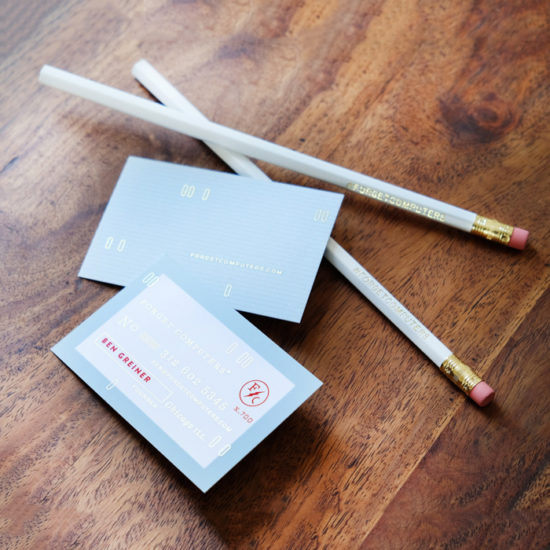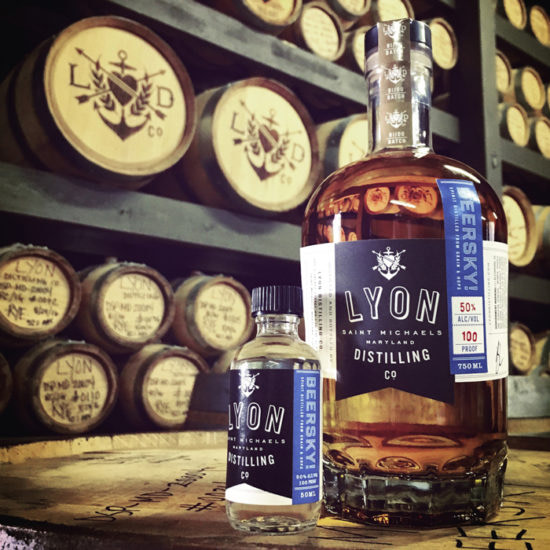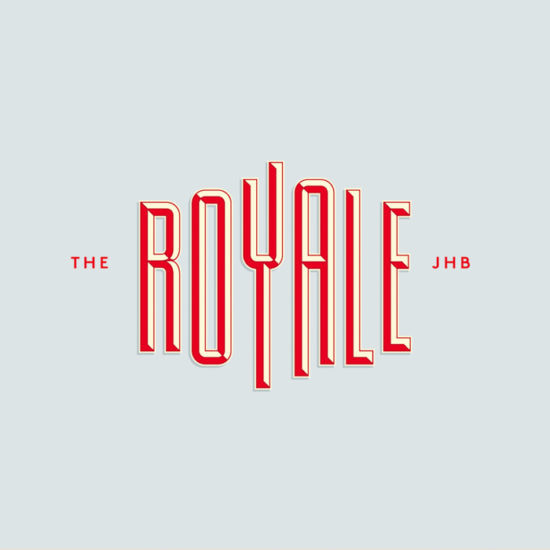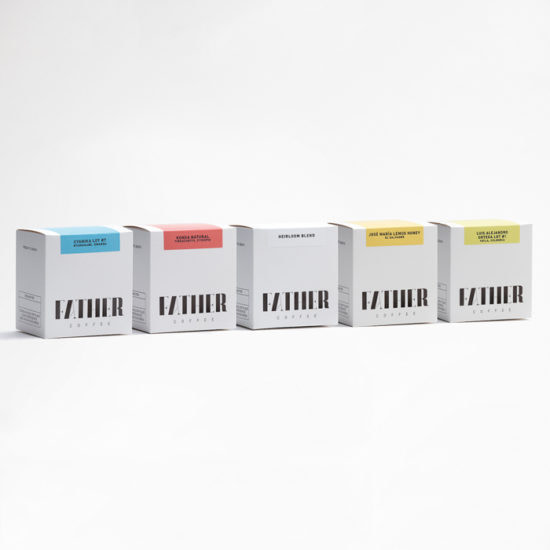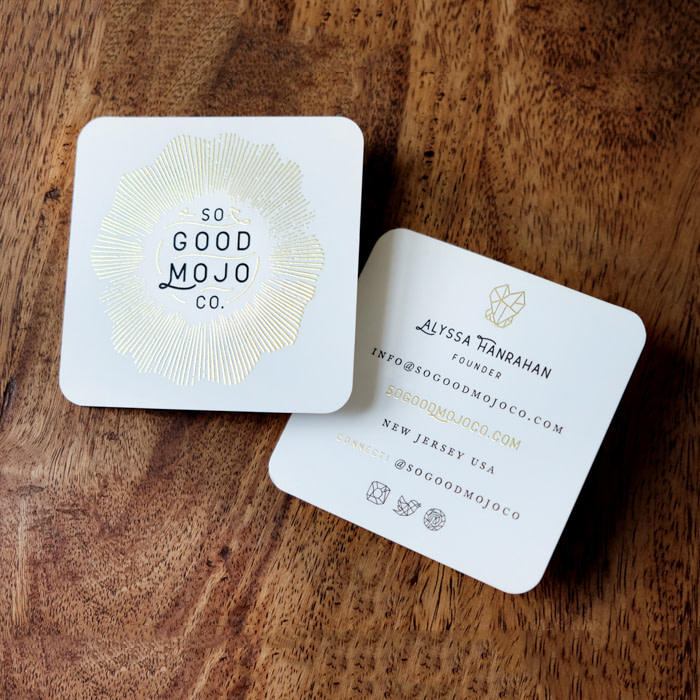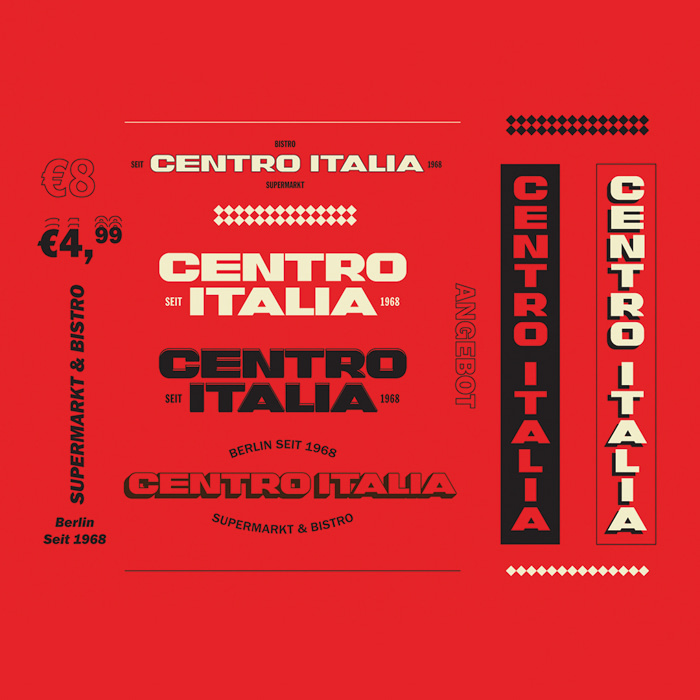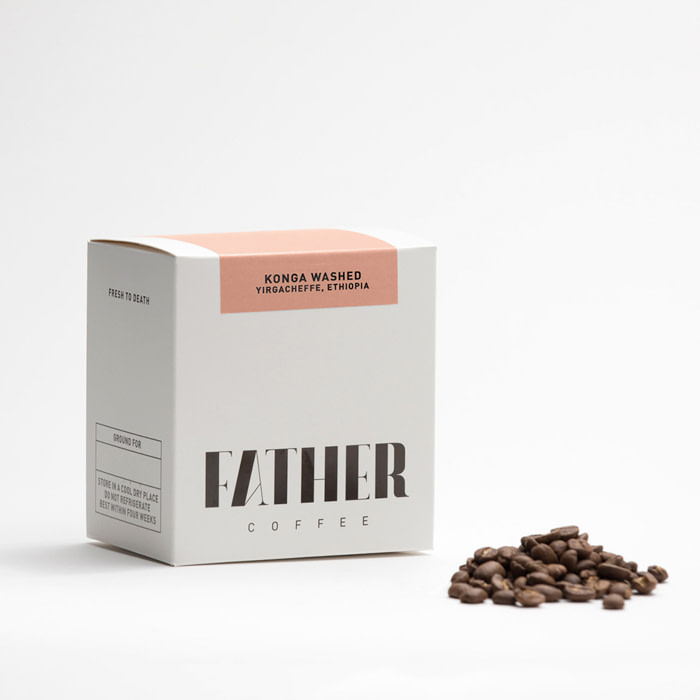
3 designer con il pallino per i font
Quanto c’è di un marchio in un font? Il motto di questi tre designer è: la parola ai font.
Cosa nasce dall’incontro fra arte tipografica e stampa di qualità? Nei Biglietti da Visita creati da questi 3 designer, i protagonisti sono i font.
Non è facile raccontare una storia all’interno di un design. Ma grazie a una miriade crescente di font nuovi di zecca, oggi i designer hanno la chance di sperimentare modalità di comunicazione inedite e originali. Il motto di questi tre designer è: la parola ai font.
Funnel
Funnel è il frutto del lavoro di Eric Kass, designer con sede a Indianapolis. Dopo anni e anni trascorsi chino sulla scrivania di un’agenzia di design, Eric si è reso conto che quello che voleva davvero era dedicare a un marchio tutto suo la cura e la passione che fino ad allora aveva riservato ai marchi dei clienti più svariati. Ispirandosi alla sua variegata collezione di stampe vintage, caratterizzate da font eclettici, Eric ha dato vita all’identità visiva di Funnel, basata su un logotipo esclusivo e font classici in abbondanza. Questa esuberante varietà tipografica esprime, per Eric, l’amore per i dettagli e il rispetto della tradizione del design.
Quando Eric si mette al lavoro sul progetto di un cliente, per prima cosa cerca di visualizzare la storia del marchio identificandone gli elementi distintivi. “Mi piace scomporre il marchio in un sistema di segni, font, colori ed elementi che danno vita al linguaggio del marchio stesso, alla sua essenza, alla sua storia”, afferma Eric. “È il primo passo, il resto viene da sé: cancelleria, sito internet, design d’interni e materiale stampato”.
Per esprimere al meglio l’identità del suo marchio, Eric ha selezionato una gamma di font e finiture che non passano inosservati. Grazie ai Biglietti da Visita con finitura Soft Touch e Stampa a caldo Oro, oggi l’immagine di Funnel risplende più che mai. “L’unicità della tipografia e del design si abbina alla finitura satinata della carta e ai rilievi dorati. La gente non solo si incuriosisce, ma vuole saperne di più”, afferma Eric.
Nicholas Christowitz
Prossima tappa: Berlino, il palcoscenico dell’astro nascente di Nicholas Christowitz. Nato e cresciuto a Johannesburg, in Sudafrica, Nicholas si è trasferito in Germania con la ferma intenzione di immergersi nel panorama artistico locale e perfezionarsi come designer. Nel 2014 ha fondato uno studio di consulenza di design, e da allora ha avuto un cliente dietro l’altro.
In una città come Berlino, con i suoi mille stimoli dal punto di vista del design, per Nicholas è stato naturale mettere alla prova la sua creatività. Negli anni, ha inanellato una serie di font assolutamente magnifici: il suo fidato archivio si arricchisce ogni volta che si mette al lavoro sul progetto di un cliente. “Ho un vero e proprio patrimonio di font e stili che consulto all’inizio di ogni progetto”, ci racconta Nicholas. “Di solito seguo l’istinto, aspetto la proverbiale scintilla”.
I Biglietti da Visita Luxe di Nicholas sono una rappresentazione tangibile di quel che si dice “lasciare la parola ai font”. Per le informazioni personali e la biografia ha scelto il font Plantin. “Ho letto assiduamente per anni la rivista Monocle, e alla fine mi sono innamorato di quel font. È semplice, elegante e piacevolmente neutro”, ci spiega Nicholas. Anche la personalità di Nicholas, semplice e sicura di sé, trova espressione nei biglietti Luxe: “Il cartoncino spesso trasmette ai clienti le mie priorità: qualità, consistenza e percezione”.
BK + Co.
BK + Co. è uno studio creativo che opera a Richmond, in Virginia. Fondato da Birdgit Kreutzer, lo studio collabora con imprenditori dalla personalità creativa: l’obiettivo è dare vita a un’identità visiva inconfondibile per ogni marchio, in grado di raccontarne la storia. Bridgit ha studiato design alla Virginia Commonwealth University e alla prestigiosa Gerrit Rietveld Academie di Amsterdam. La sua passione per il design l’ha spinta a creare un’attività tutta sua, con l’ispirazione e il sostegno della comunità di creativi di Richmond. “Qui la norma è esplorare strade nuove, sostenendoci a vicenda”, racconta Bridgit.
Aprire uno studio di design si è rivelato una scelta appagante. “Lavorare e collaborare con i clienti è un privilegio, per me. Ogni nuovo progetto è una sfida a sé stante, che mi stimola a giocare con nuove idee”. Tutti i progetti sono diversi fra di loro. Il primo passo, per Bridgit, è concentrarsi sul font.
Di recente ha lavorato su un progetto per un massoterapista. Il cliente desiderava un design che trasmettesse calma, tranquillità e l’idea di un legame genuino con la natura. Bridgit ha optato per un carattere tipografico classico e pulito: il complemento ideale per il resto della grafica, improntato alla semplicità. Per la stampa ha scelto i Biglietti da Visita Luxe, la cui finitura opaca si sposa ai colori tenui del marchio. “Guardando questi biglietti mi sento serena, come se respirassi meglio”, afferma Bridgit. A volte basta il font giusto per creare un’emozione.